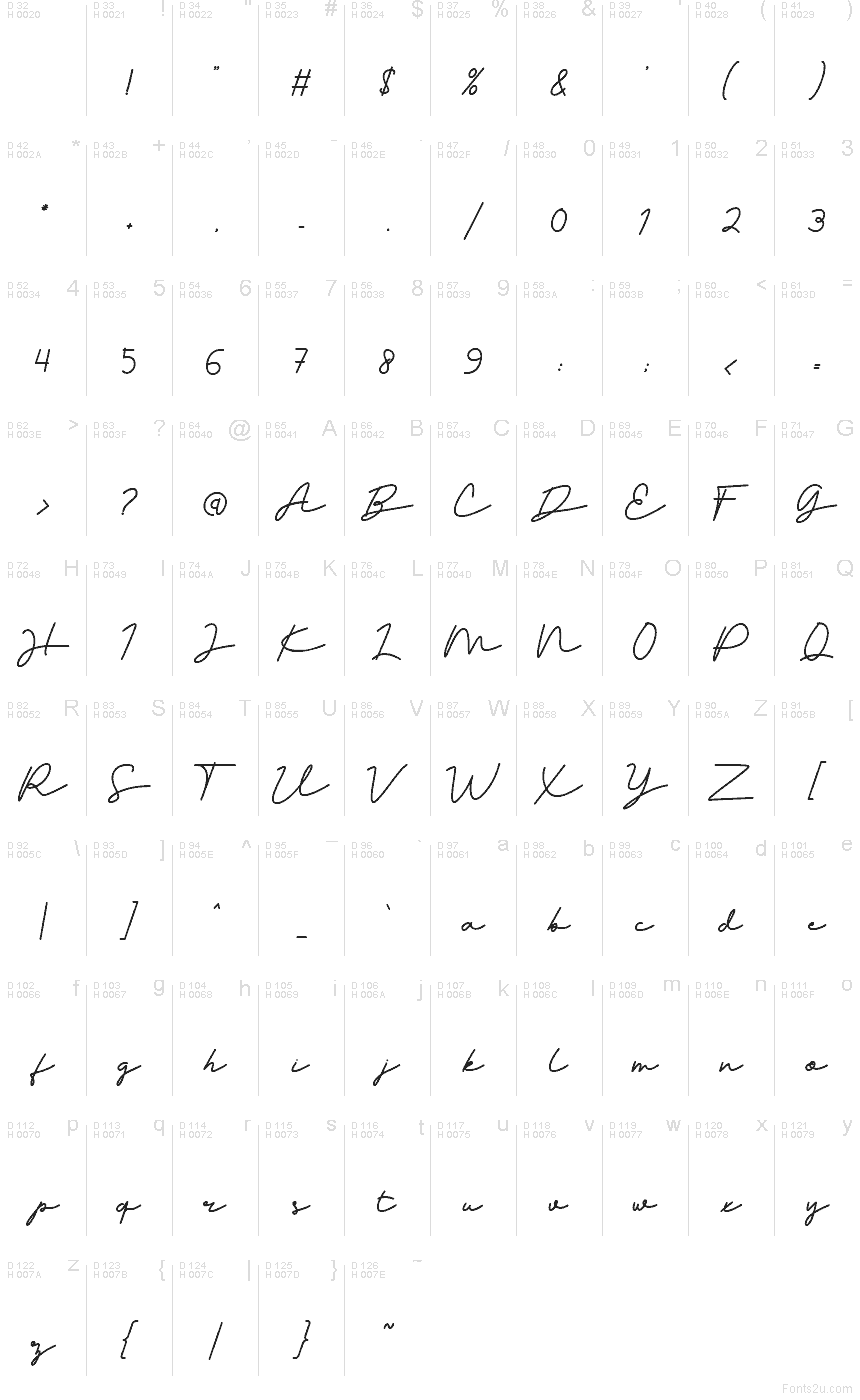
Faded Glory Script від Putracetol Studio - це безкоштовний рукописний шрифт, що вирізняється плавним курсивним ритмом та високими петлями, які надають йому легкості та повітряності. Довгий початковий штрих та м’які овальні форми надають дизайну розслабленого вигляду в стилі ручного розпису вивісок, уникаючи надмірної грубості, притаманної шрифтам під пензель.
Він чудово виглядає в логотипах бутиків, на пакованнях товарів, у меню кав'ярень, цитатах для соцмереж та весільній поліграфії, де рівний рукописний стиль виглядає індивідуально, не перевантажуючи дизайн. Плавний рух і подовжений початковий штрих надають коротким заголовкам та брендингу на основі імен витонченості, що ідеально підходить для етикеток, бірок та підписів.